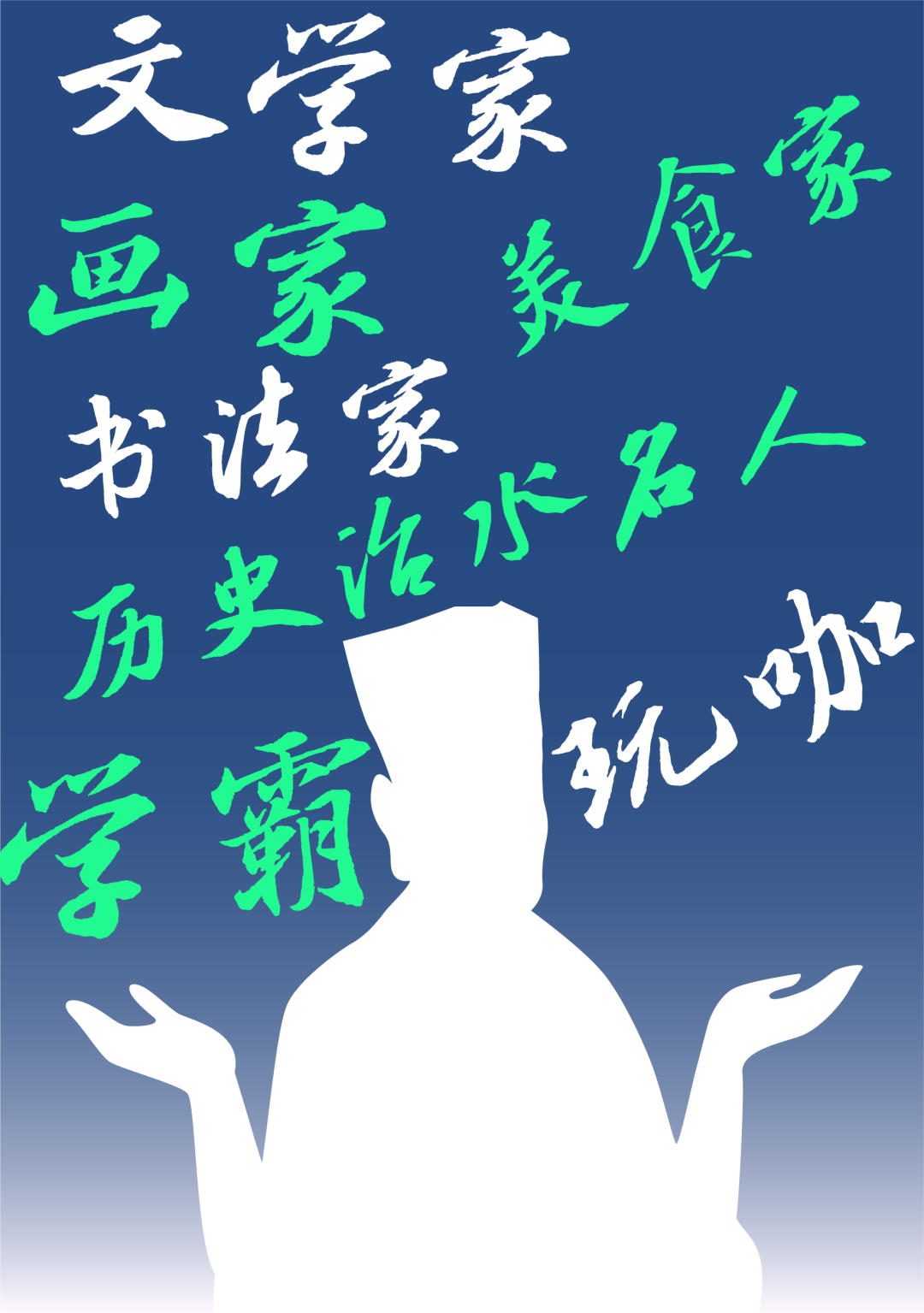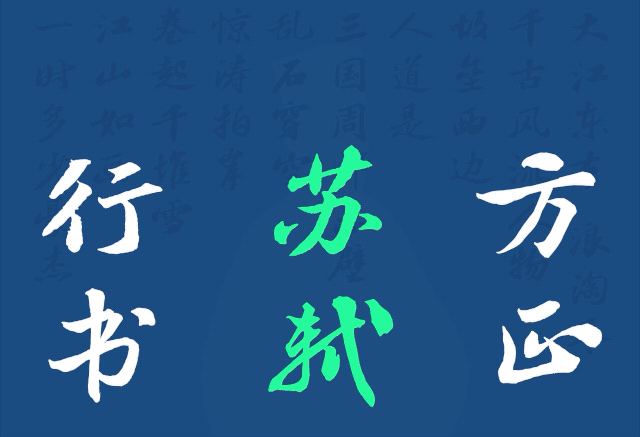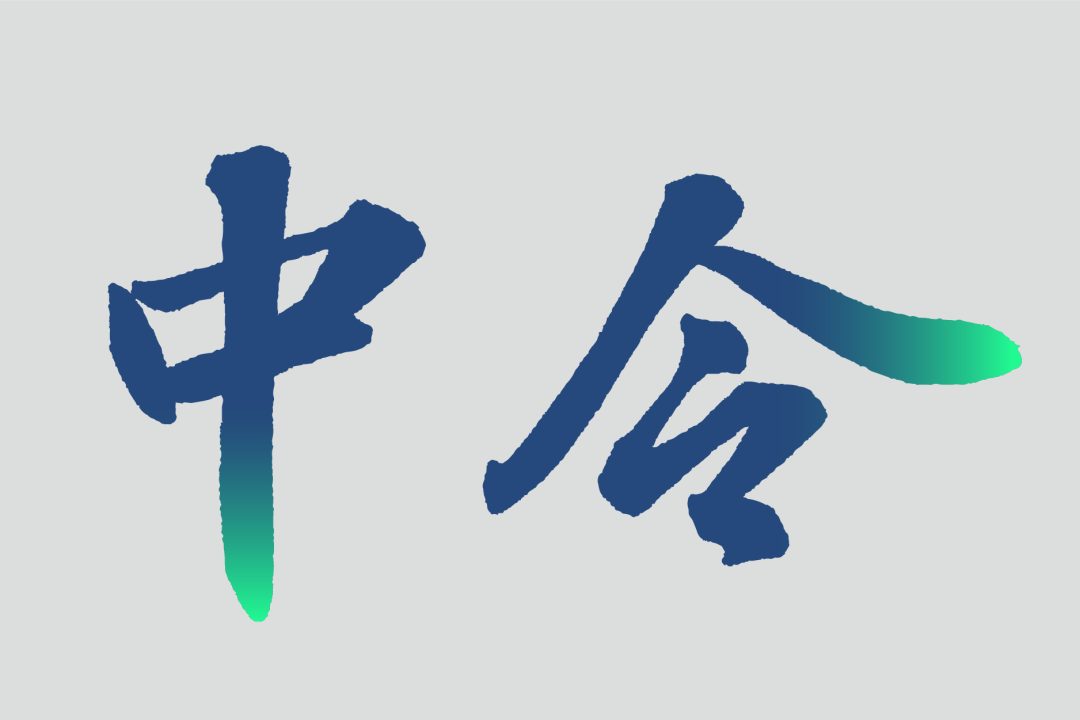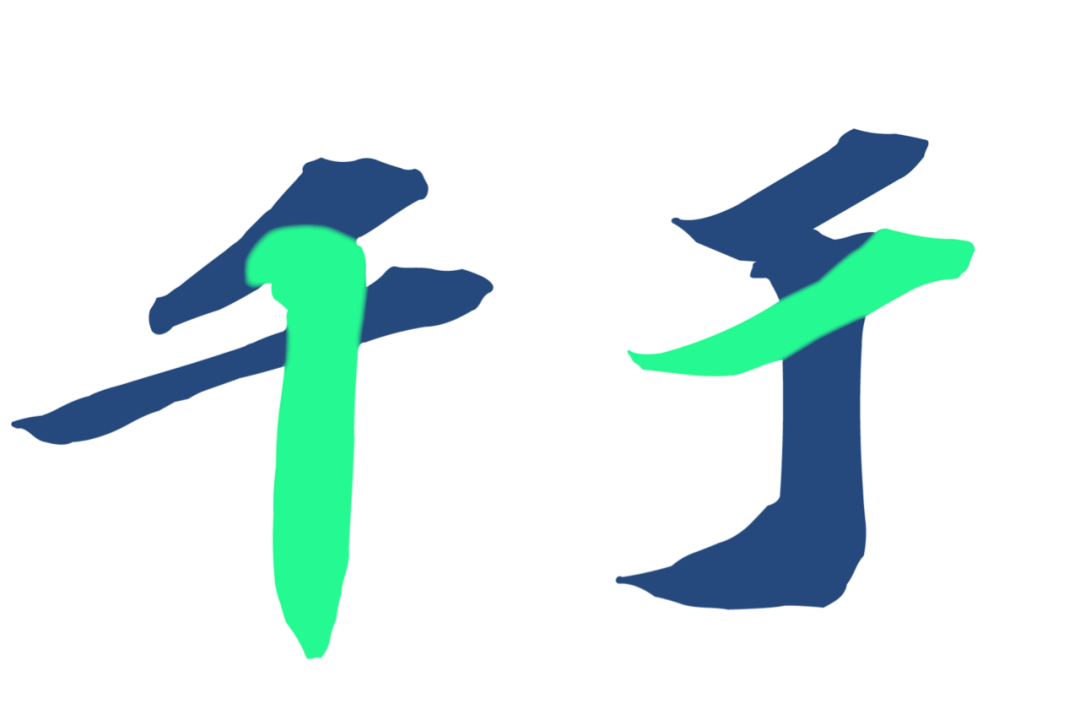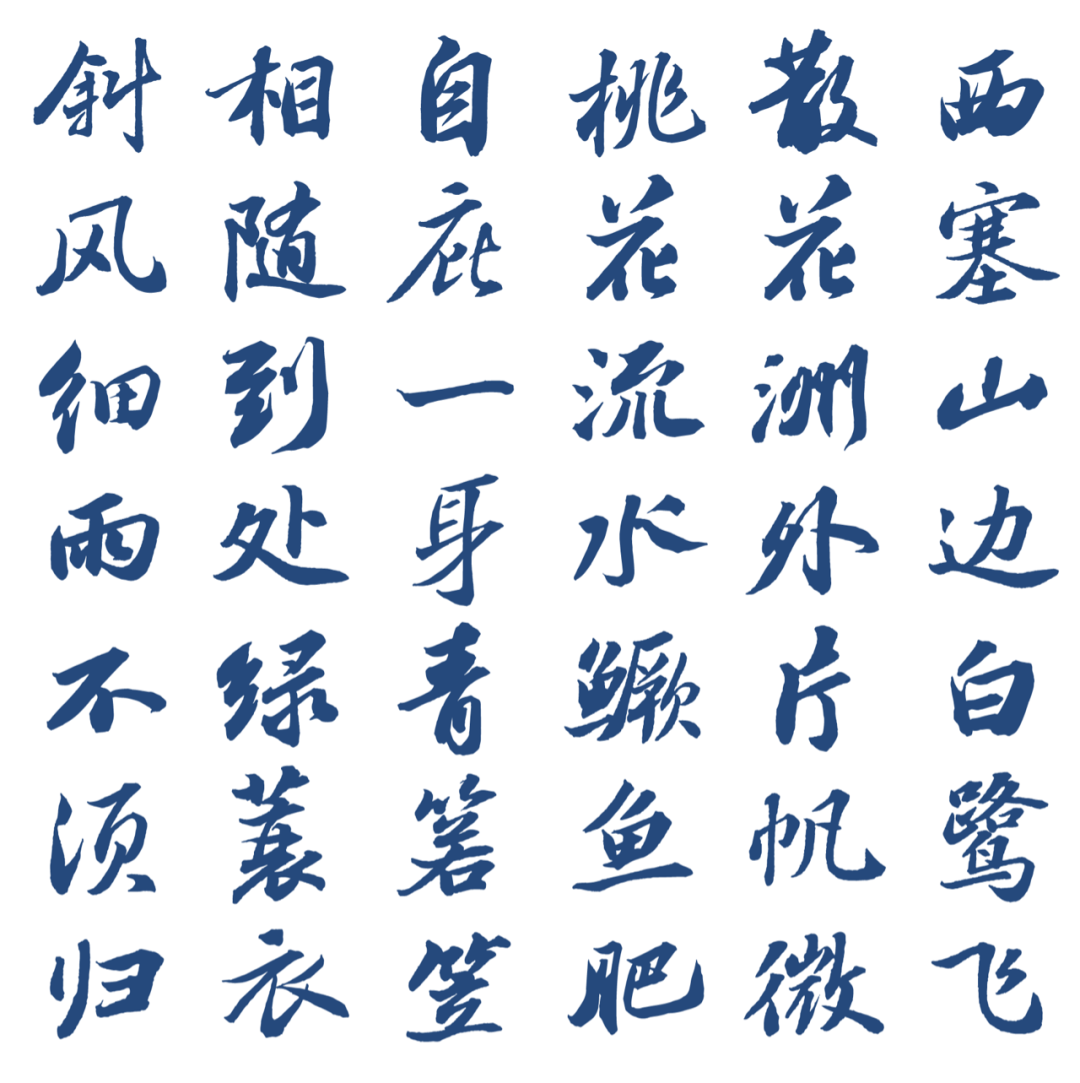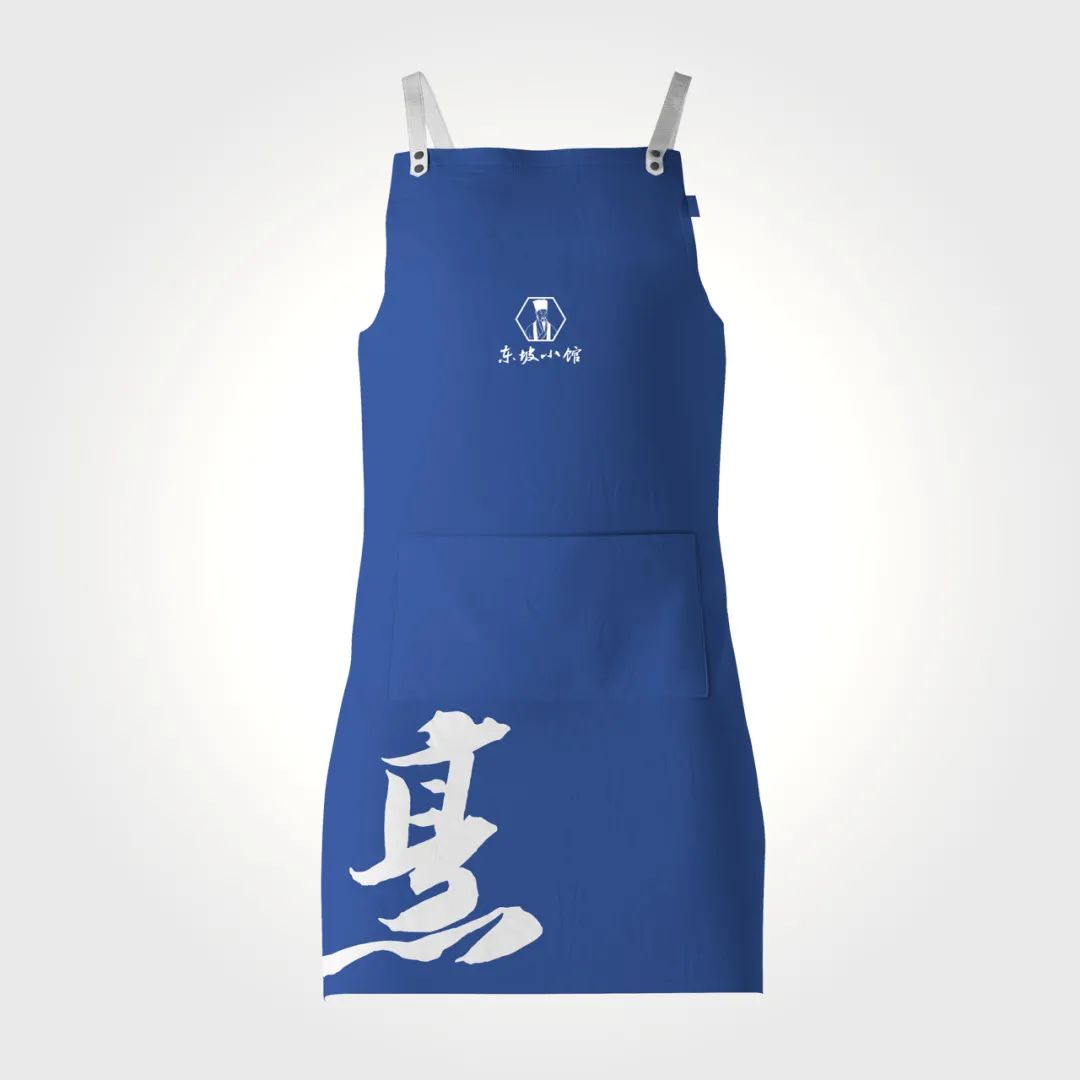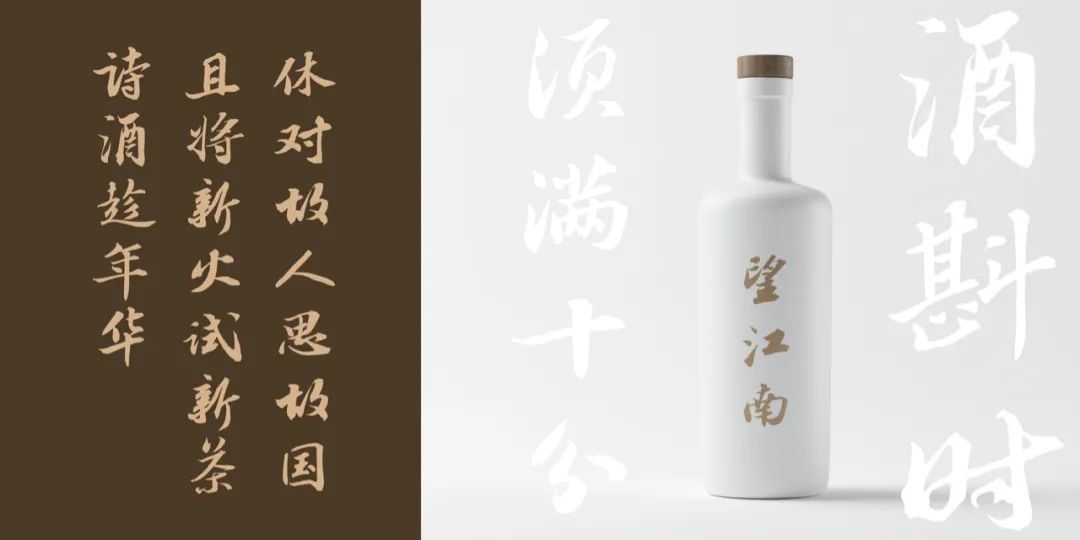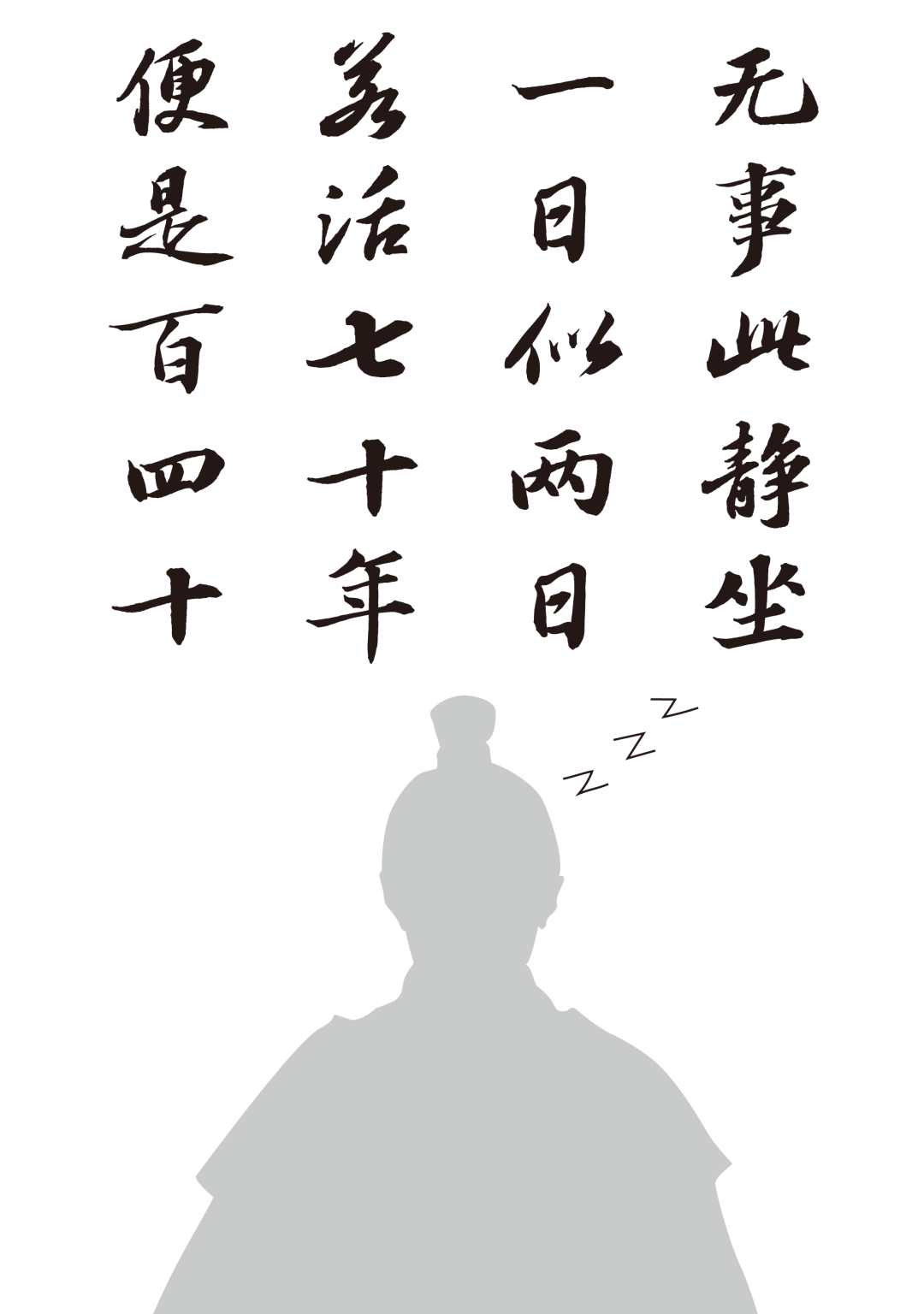
方正苏轼行书
字体品牌: 方正字库 中华精品字库 整理/设计:仇寅 字体分类:行书 字体属性:精品字 字符集:简繁扩展(GBK)、大陆简体(GB2312-80) 发布时间: 2020
·字体特征
以苏轼字帖(信札、手卷)、刻帖为开发依据。笔法丰腴、结字扁平,横轻竖重、撇捺舒展,随形变化、错落有致,体现了自然率真、拙朴敦厚的深蕴。
·关于苏轼
苏轼(1037-1101),北宋文学家、书画家。字子瞻,号东坡居士,眉州眉山(今属四川)人。其文汪洋恣意,明白畅达,为唐宋八大家之一。其诗清新豪健,善用夸张比喻,在艺术表现方面独具风格。擅长行书、楷书,取法李邕、徐浩、颜真卿、杨凝式,而能自创新意。用笔丰腴跌宕,有天真烂漫之趣。存世书迹有《答谢民师论文帖》、《祭黄幾道文》、《前赤壁赋》、《黄州寒食诗帖》等。
2020年恰逢故宫博物院600岁生日,作为开场人物,苏东坡以“千古风流人物”的形象亮相。
虽然如此,这位文艺界大V丝毫没有偶像的包袱…… 他是我们吃货的信仰,“日啖荔枝三百颗”,暴饮暴食没在怕。
他独创怪诞养生之法:餐后拍着肚皮来回走。有天他问身边人,“你们且说,此中藏有何物。”
他有奇葩的长寿秘诀:“无事此静坐,一日似两日。若活七十年,便是百四十。”
他给我们情感的慰藉,“天涯何处无芳草”,下一个会更好。
他和我们一样。 夜深也会开启“网抑云”模式:“此生此夜不长好,明月明年何处看。”“世事一场大梦,人生几度秋凉?”
他是苏东坡,著名的文学家、画家、书法家、历史治水名人、美食家,名副其实的斜杠青年。做得了学霸,也当得起玩咖。
方正苏轼行书充满妩媚、天真而又敦厚的韵味。